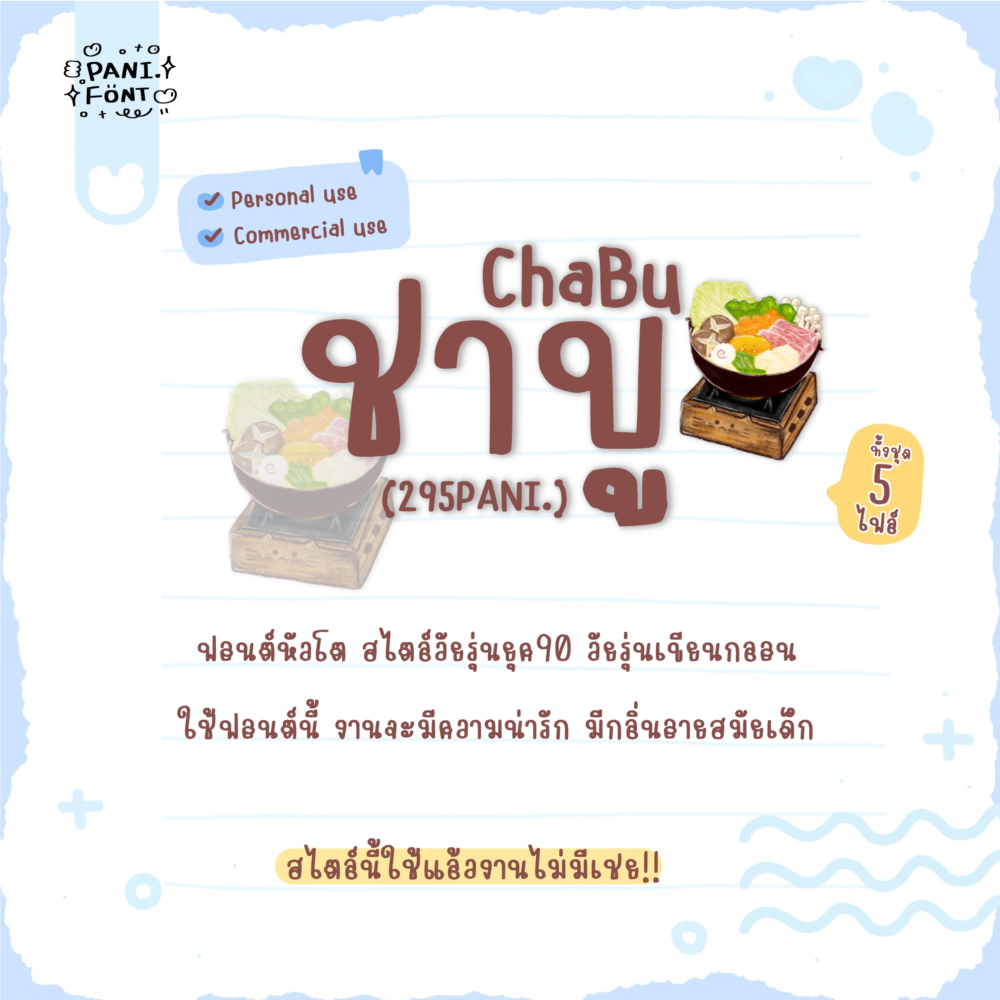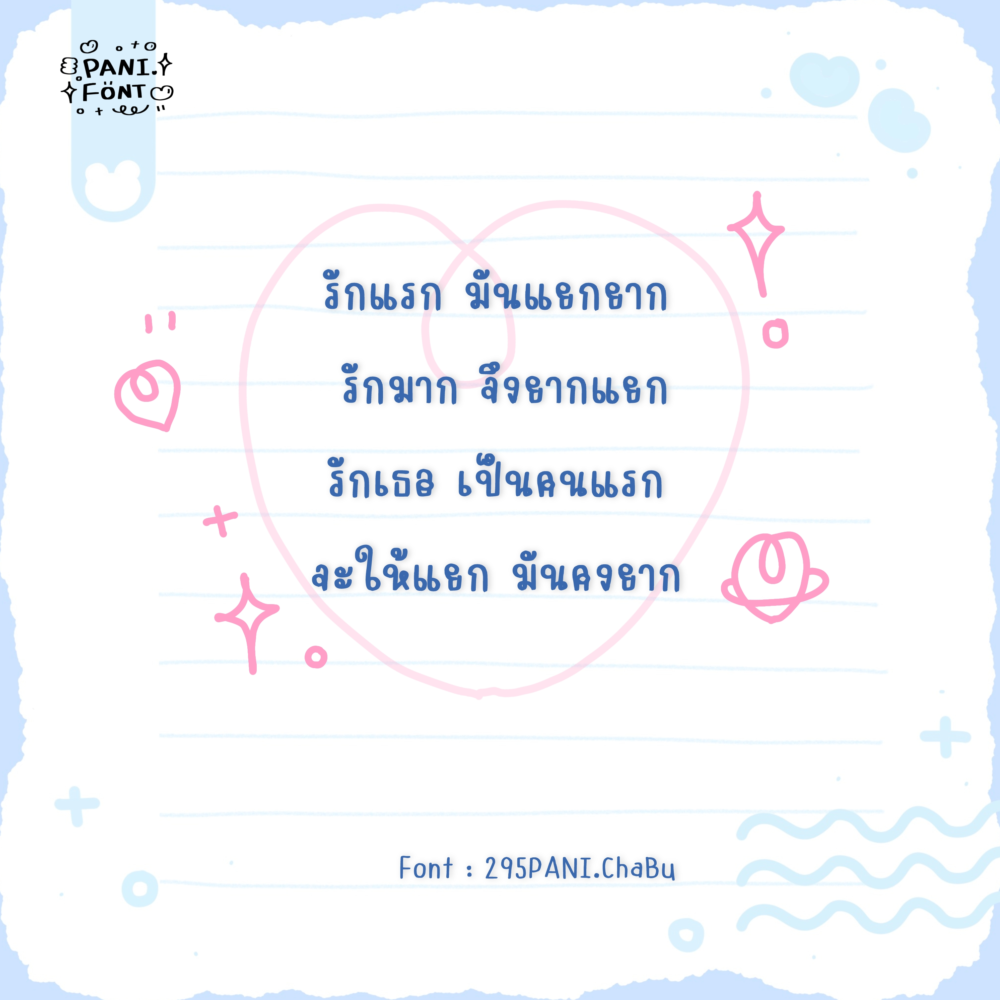
ชาบู
ฟอนต์ชาบู ชื่อฟอนต์ชวนหิว
ฟอนต์หัวโต สไตล์วัยรุ่นยุค90 วัยรุ่นเขียนกลอน
ใช้ฟอนต์นี้ งานจะมีความน่ารัก มีกลิ่นไอสมัยเด็ก
*แอนทำเส้นแบนให้เพิ่มด้วยค่ะ ชุดนี้จุกๆคุ้มๆเลย
จะตั้งเครื่อง ก็น่ารัก/อ่านรายละเอียดก็สบายตา เก๋ๆ/แต่งภาพ ก็เด่นสะดุดตา ครบเครื่อง ไม่ซ้ำใคร!